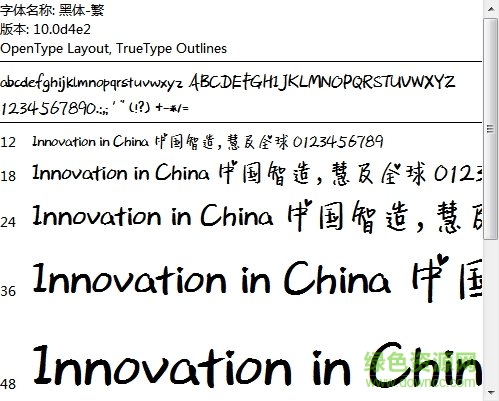
涼茶字體
涼茶字體是一款十分出彩的藝術(shù)手寫字體,有著十分流暢細(xì)膩的筆觸,干凈簡潔的結(jié)構(gòu),更有可愛的心型點(diǎn)綴讓你的文字更加生動(dòng),很有毛筆書法字體的風(fēng)格特色,喜歡的朋友就來綠色資源網(wǎng)下載收藏吧!
涼茶體特色
涼茶字體帶有小清新的愛心設(shè)計(jì)讓其在廣告設(shè)計(jì)、網(wǎng)頁設(shè)計(jì)、包裝設(shè)計(jì)等領(lǐng)域均有著不錯(cuò)的視覺效果,是一款非常清秀美觀的字體!
涼茶字體完整不缺字,能滿足廣大設(shè)計(jì)師們的日常生活需要,支持繁簡體輸入,有著十分獨(dú)特的藝術(shù)效果,相信你一定會(huì)喜歡!